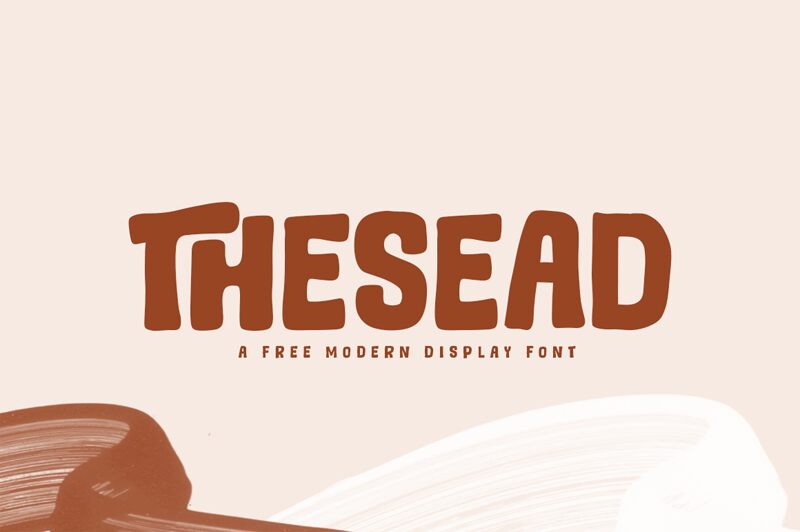
Thesead
Písmo Thesead od Khurasan & Jalembe je bezplatný font typu display v kreslenom štýle so zaoblenými, masívnymi tvarmi a mäkkými rohmi, ktoré písmenám dodávajú stlačený vzhľad ako vyrezaný z papiera. Opakujúce sa výrazné tvary a hladké krivky udržujú dizajn neformálny a grafický, bez potreby pridávať ďalšie detaily.
Thesead skvele funguje pre komiksové tituly, detské plagáty, obaly hračiek, návrhy nálepiek, pozvánky na akcie a výrazné logá. Tento bezplatný font prináša rovnakú zaoblenú energiu do krátkych textov, kde jeho jednoduché tvary ľahko unesú hlavný text, popisok alebo obálku bez potreby ďalších ozdôb.